가지고 있으면 여러모로 쓸 일이 많은 폰트! 필요한 곳에 어울리는 폰트를 넣어 무언가를 완성 시켰을 때의 그 짜릿함이란.. 폰트를 많이 가지고 있으면 보물상자를 가진 것도 같죠. 오늘은 에디터가 자주 사용하면서 도움 잔뜩 받은 무료 폰트 사이트를 공유할게요. 영어부터 한글, 상업용 무료 폰트까지 다~ 있으니 집중!
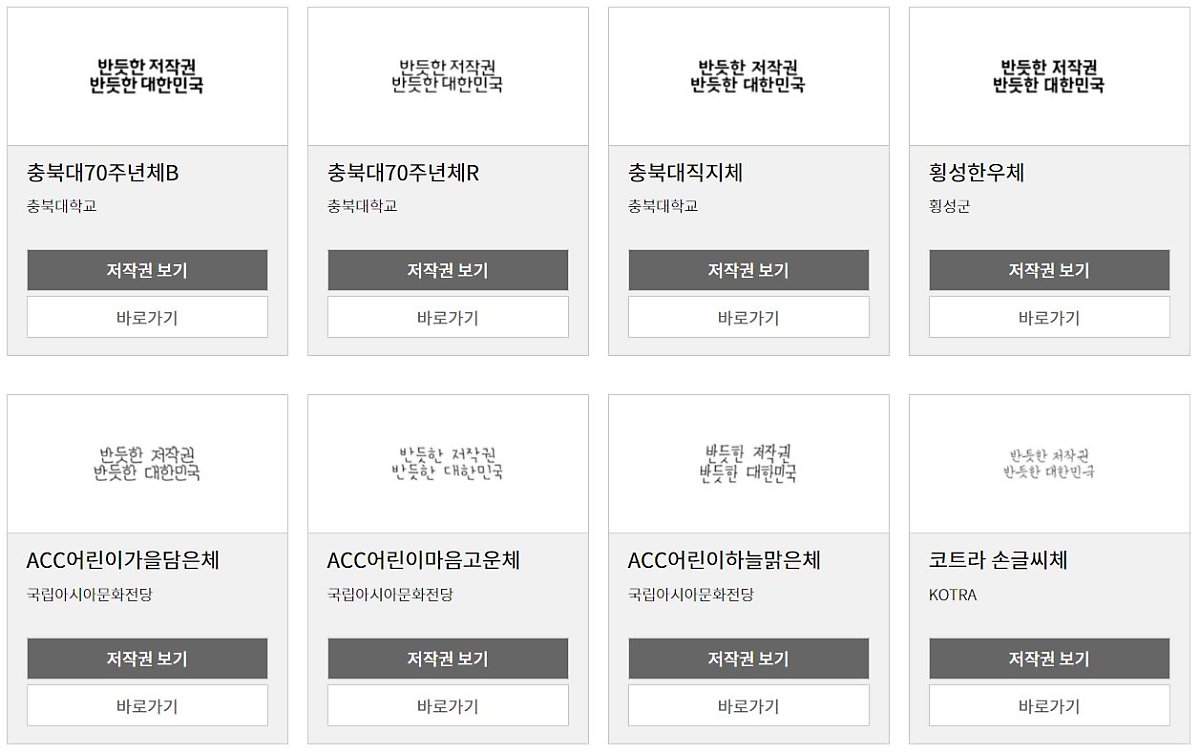
공유마당 무료폰트
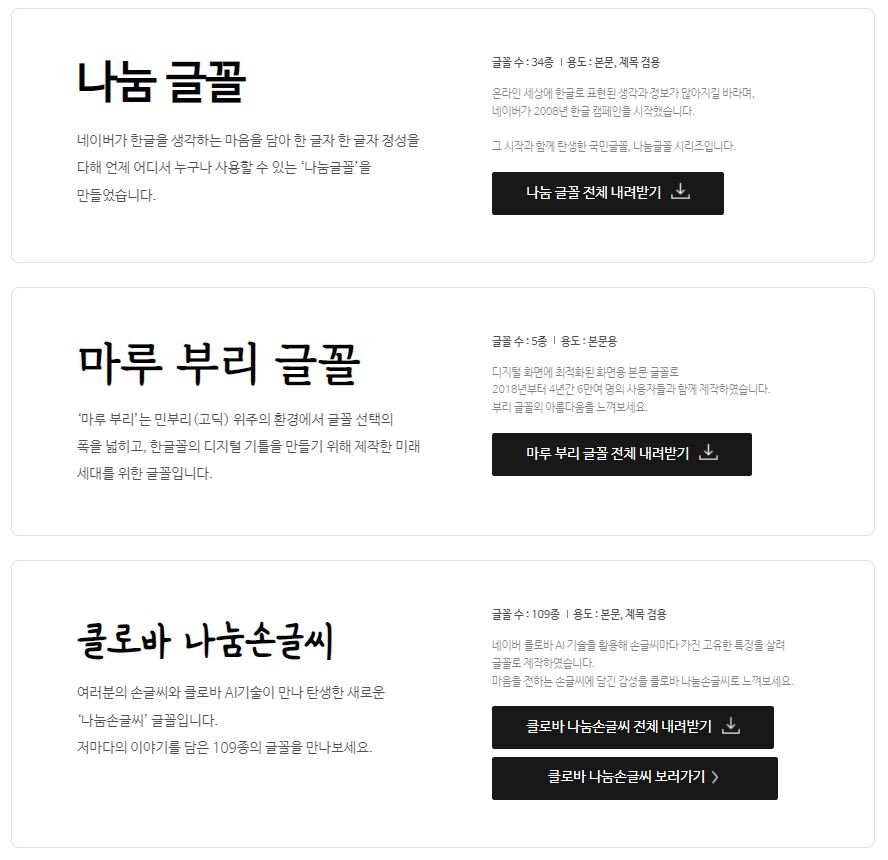
네이버 글꼴 모음
매우 잘 만들어진 데다 개인 및 기업 사용자를 포함한 모든 사용자에게 무료로 제공되는 네이버 글꼴! 벌써 세 가지 글꼴이 나왔어요. 유료로 판매하지만 않으면 상업적인 이용이 가능하다는 것이 장점이에요.
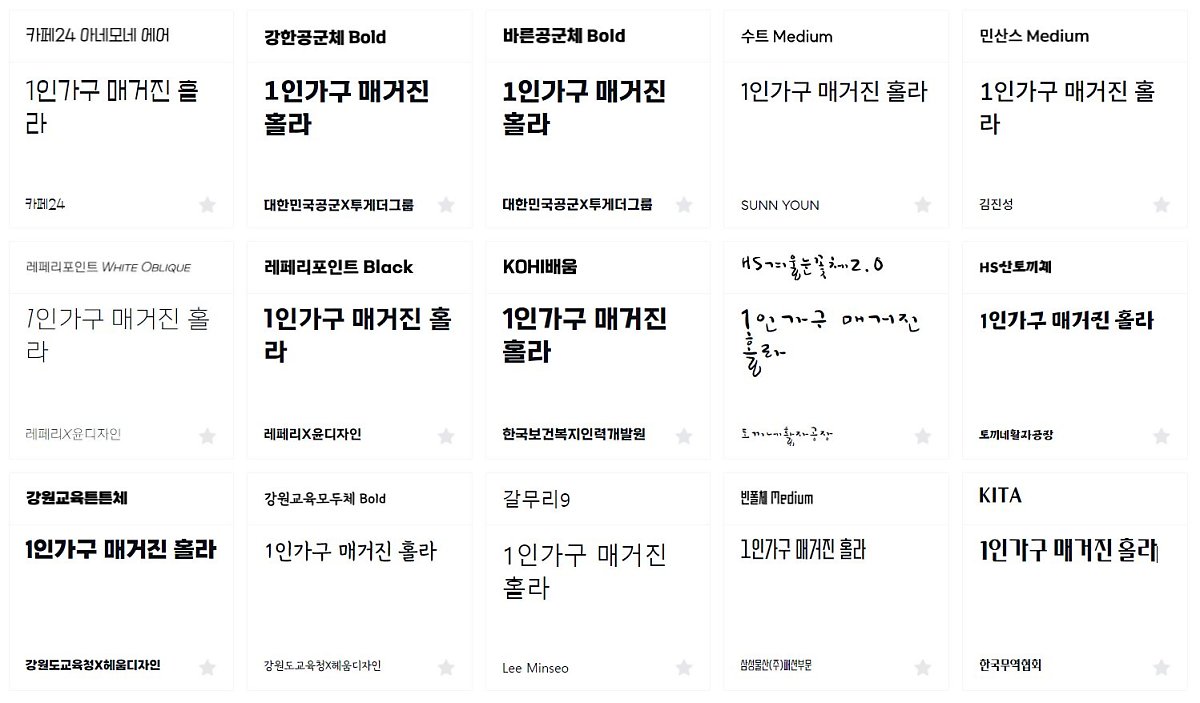
눈누
눈누는 상업적으로 이용할 수 있는 한글 폰트 중에서도 잘 알려지지 않은 폰트를 소개하는 사이트예요. 정말 다양하고 예쁜 폰트가 있는 데다, 저작권을 확인하고 다운로드하는 방법이 간단해서 편리해요. 게다가 폰트가 적용되어야 하는 문장, 단어를 직접 써보고 한눈에 비교할 수 있다는 것도 매력적이에요.
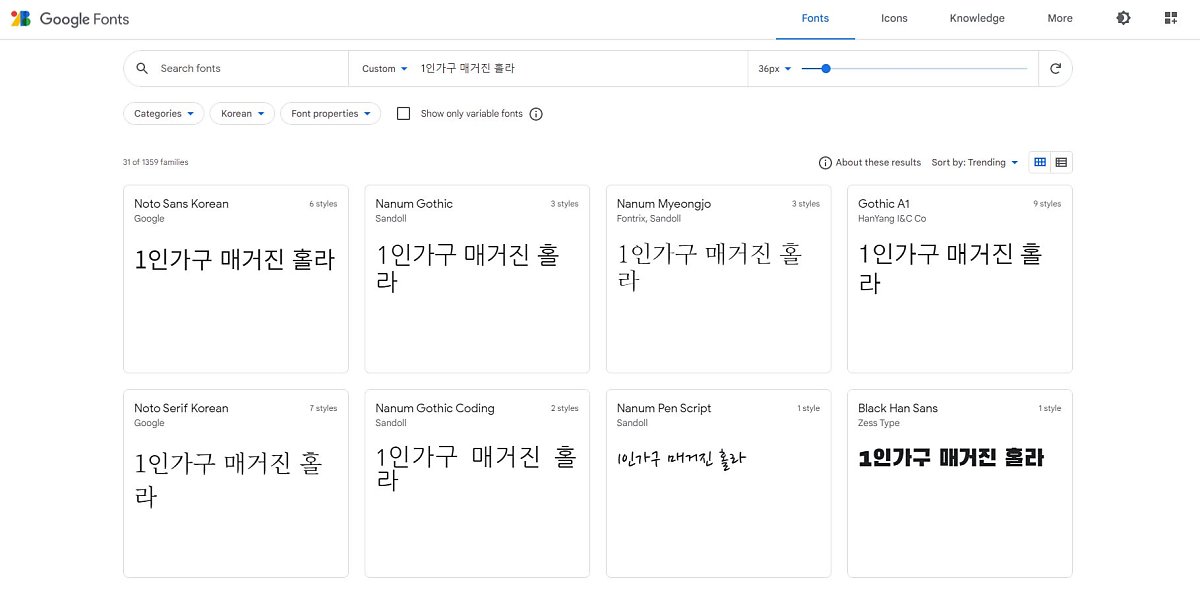
구글 폰트 (Google Fonts)
구글에서 제공하는 무료 폰트 다운로드 사이트입니다. 주로 특정 폰트를 다운로드하기 위해 사용돼요. 대표적으로 Noto Sans와 Black Han Sans가 있습니다. 두 폰트는 모두 상업적 이용이 가능하고 폰트 굵기도 다양해서 여러모로 쓰기 좋아요. 모든 폰트는 License(저작권)을 확인하고 다운로드 받으시기를 추천합니다!
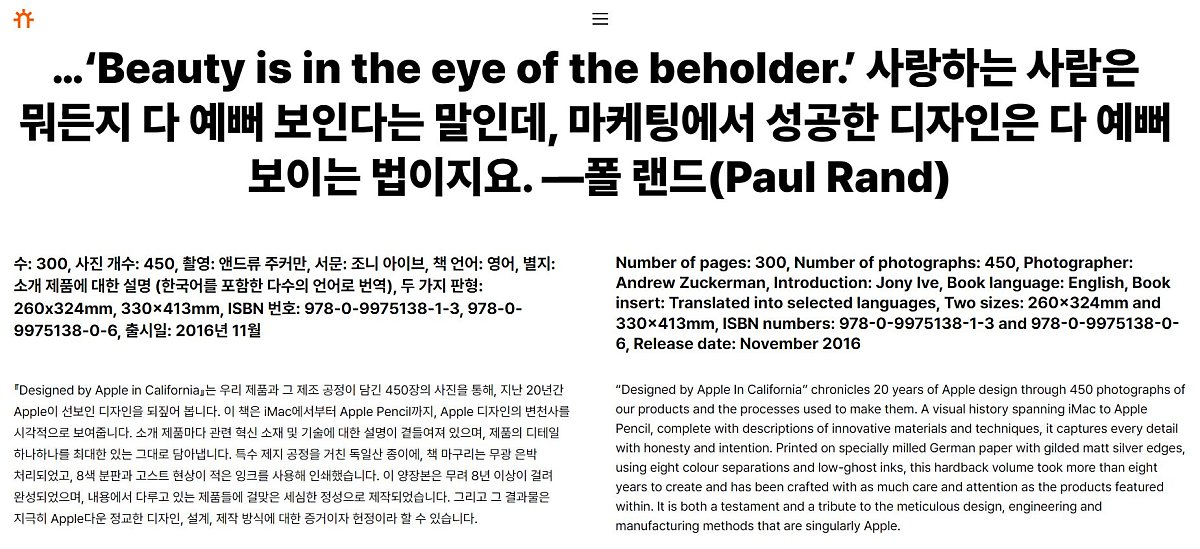
Pretendard
Apple의 기본 폰트를 다른 곳에서도 보고 싶어 만들어졌다는 프리텐다드 글꼴! 사이트에 들어가서 보아도 애플 유저라면 마음이 편-안 해집니다. 총 9개의 굵기로 이루어져 본문 전체에 사용할 수 있는데요. 영문과 한글, 숫자, 이모티콘, 그 외 다양한 언어에도 적용이 되어 행복해요. 게다가 상업용으로도 사용이 가능하다는 거!
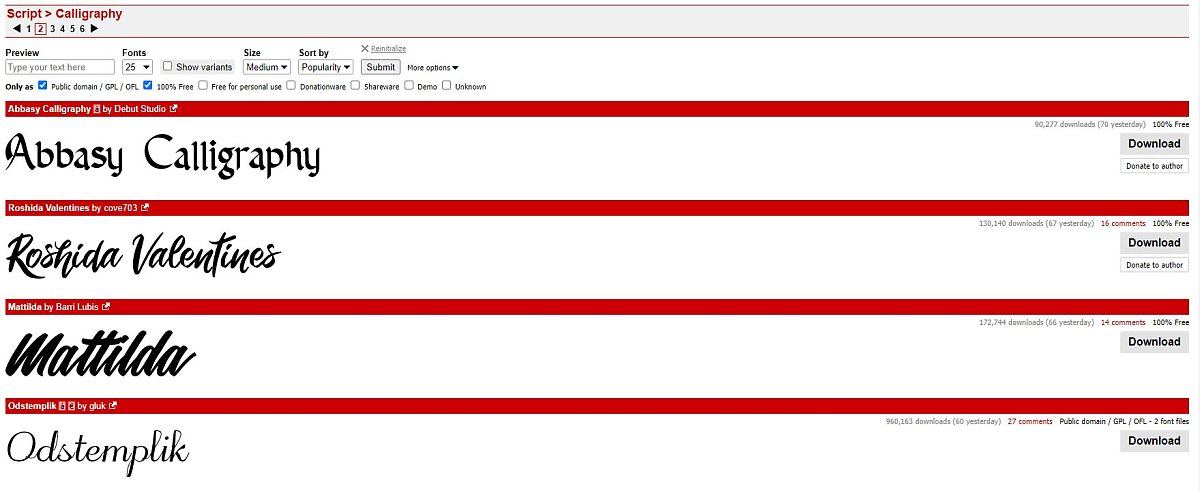
dafont.com
캘리그라피 같이 어딘가 더 멋진 영문 폰트를 찾느라 고생 중이셨다면, dafont를 추천해요. 몇 가지 단계만 거치면 쉽게 무료 폰트를 찾을 수 있어요. 원하는 테마를 클릭하고, 폰트 목록 상단 More options 클릭, 100% Free를 선택, Submit을 클릭하면 돼요. 단, 상업용으로 사용하려면 폰트별 Note of the author를 확인하세요.